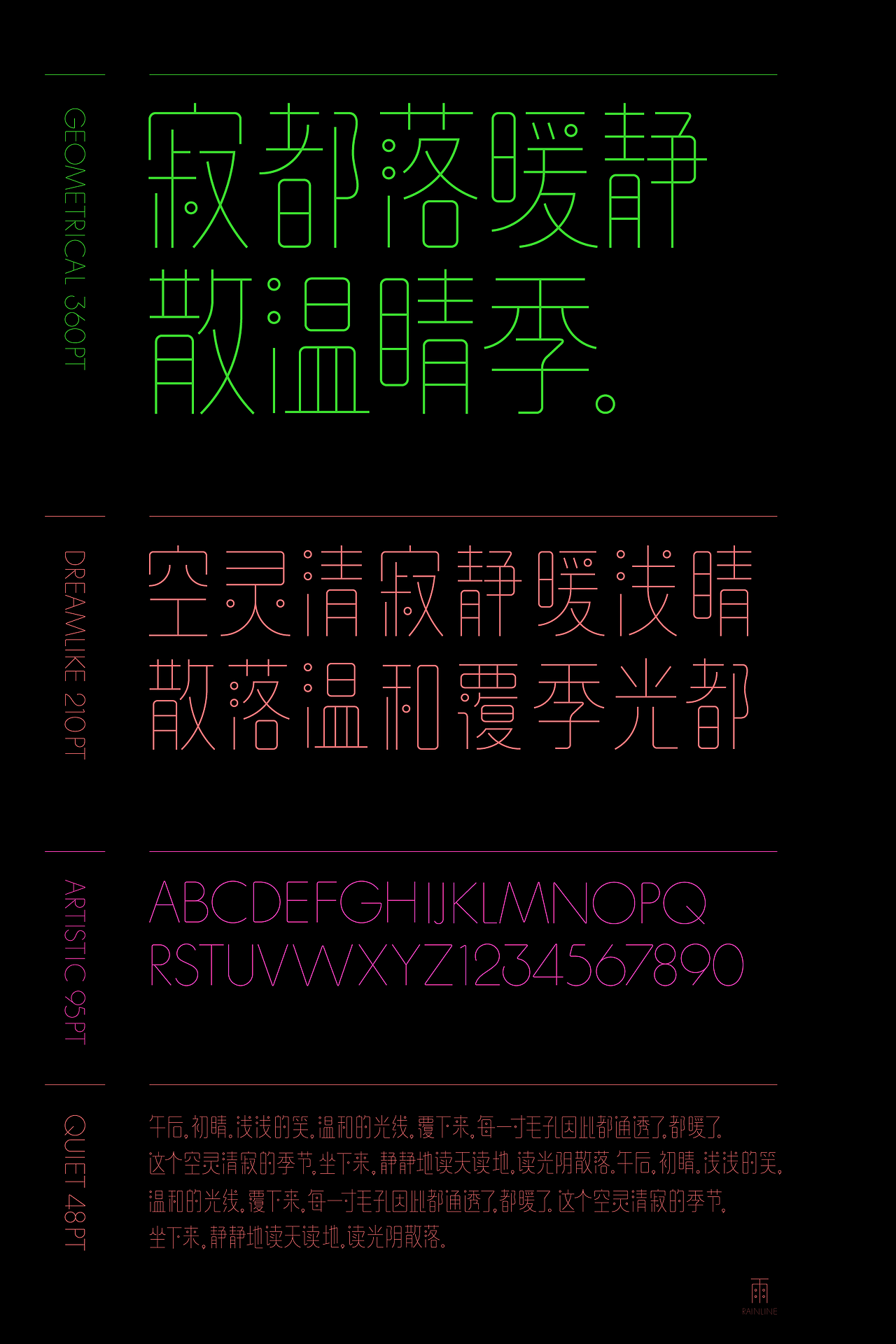
雨线体/RainLine
雨线体 / rainline
点像雨,故得名;体瘦长,取篆意。
The dots look like raindrops, and all the strokes are lines and circles. So it is named rainline.
As we know, the strokes of Chinese characters almost are random geometry, but here they are given order, only lines and circles. The characters are strictly limited in rectangle. Every single structure are broken and rebuilt, and it should be read and beautiful.